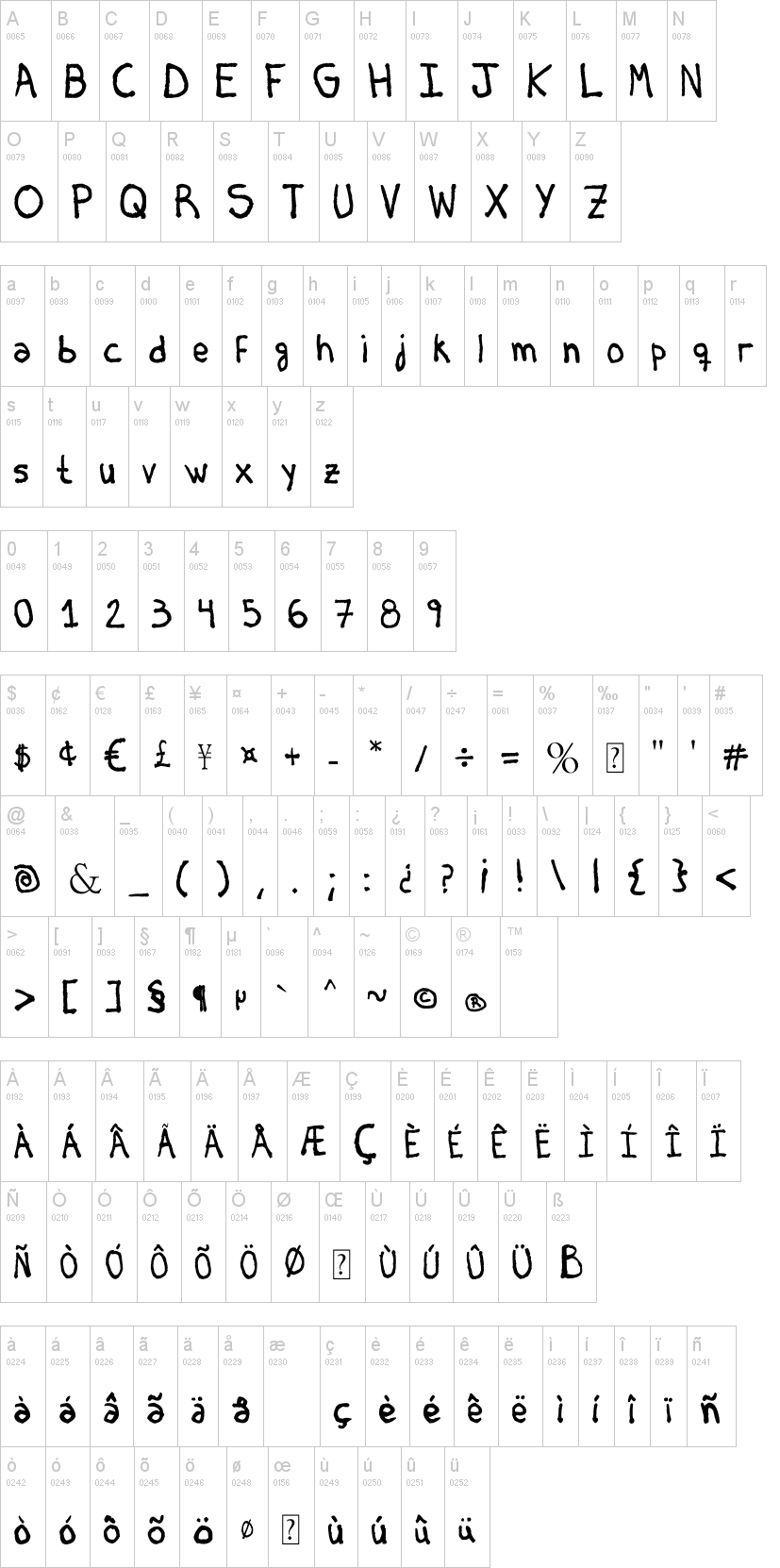
Briasco Rustic
Briasco Rustic 是一款古典主义风格的字体,它具有粗犷而优雅的外观,具有粗犷的线条和细节,并且具有浓郁的历史感。它的字形具有清晰的细节,使其在印刷和屏幕上都能够清晰地显示,并且具有出色的可读性。Briasco Rustic 可以用于多种用途,包括标题、标签、标识、标志等。
Briasco Rustic是一款非常不错的手写艺术字体,具有很好的视觉感,适合于文化类的宣传设计、商业类品牌的广告和产品包装设计以及个性化文字排版等较多场景。